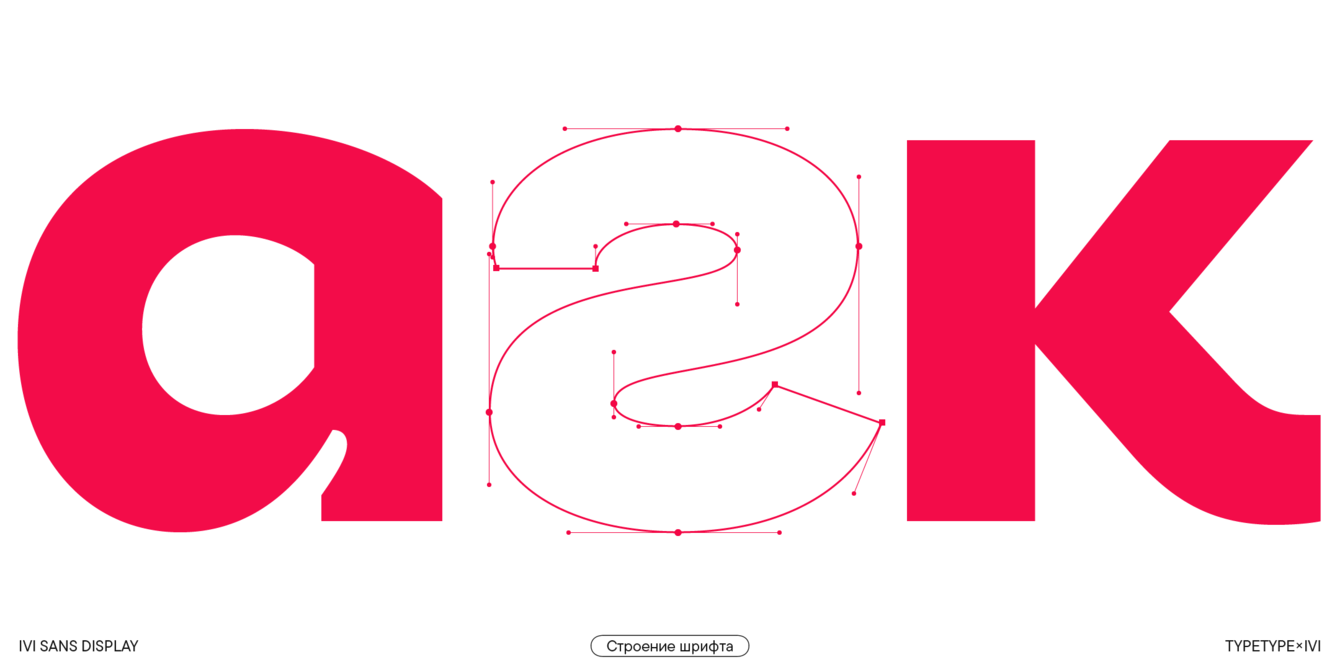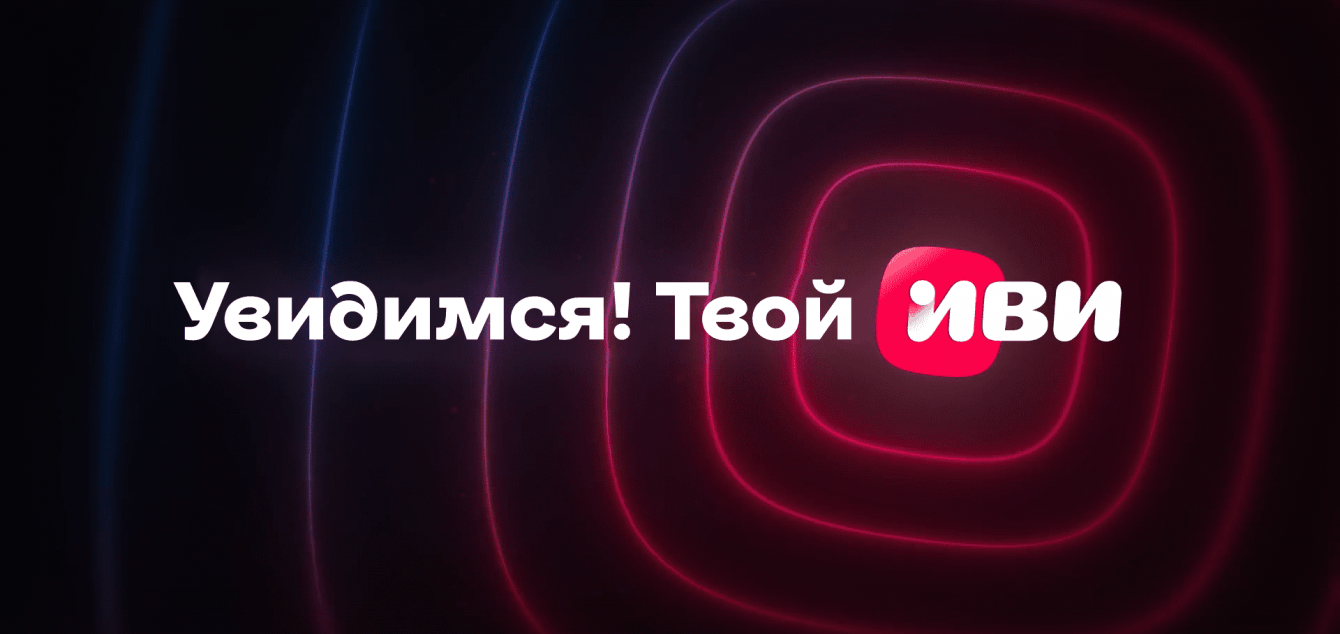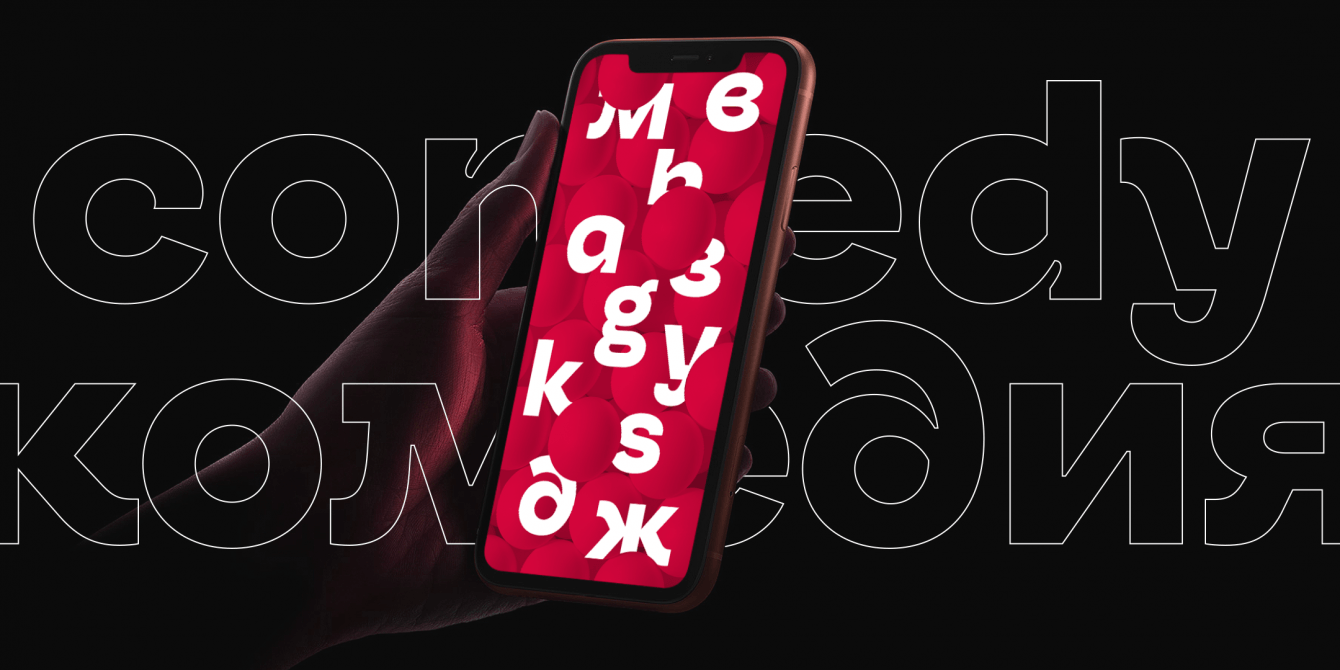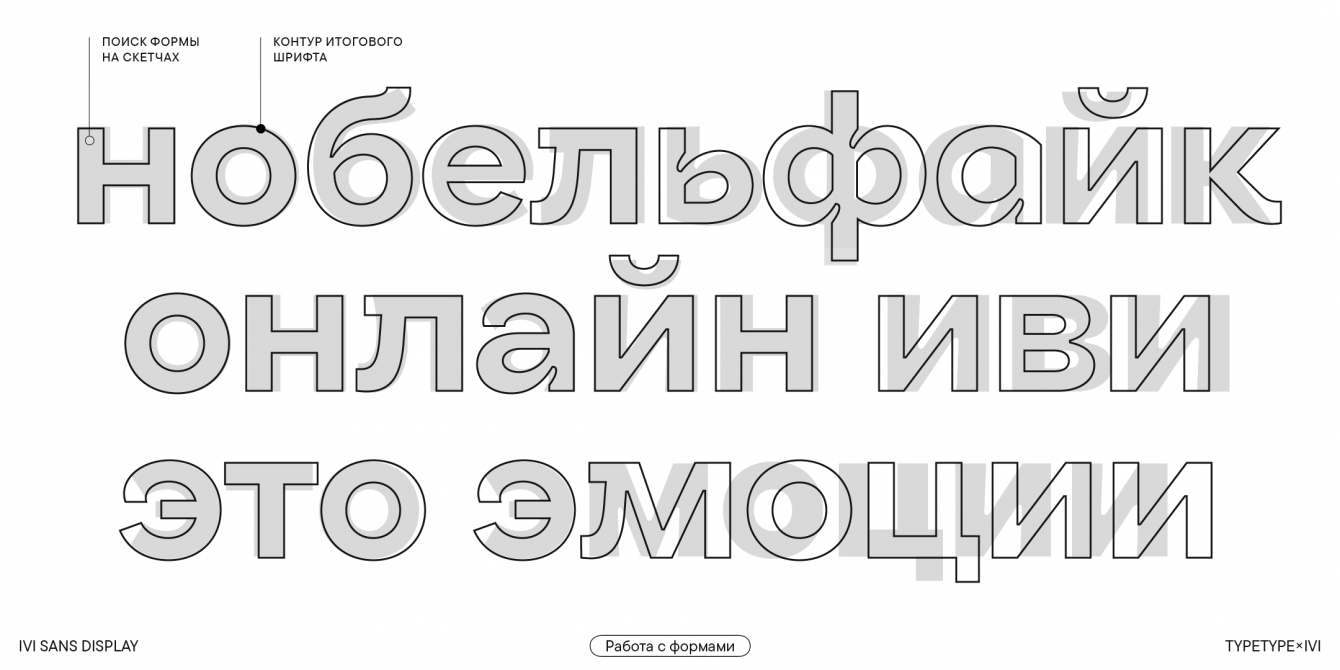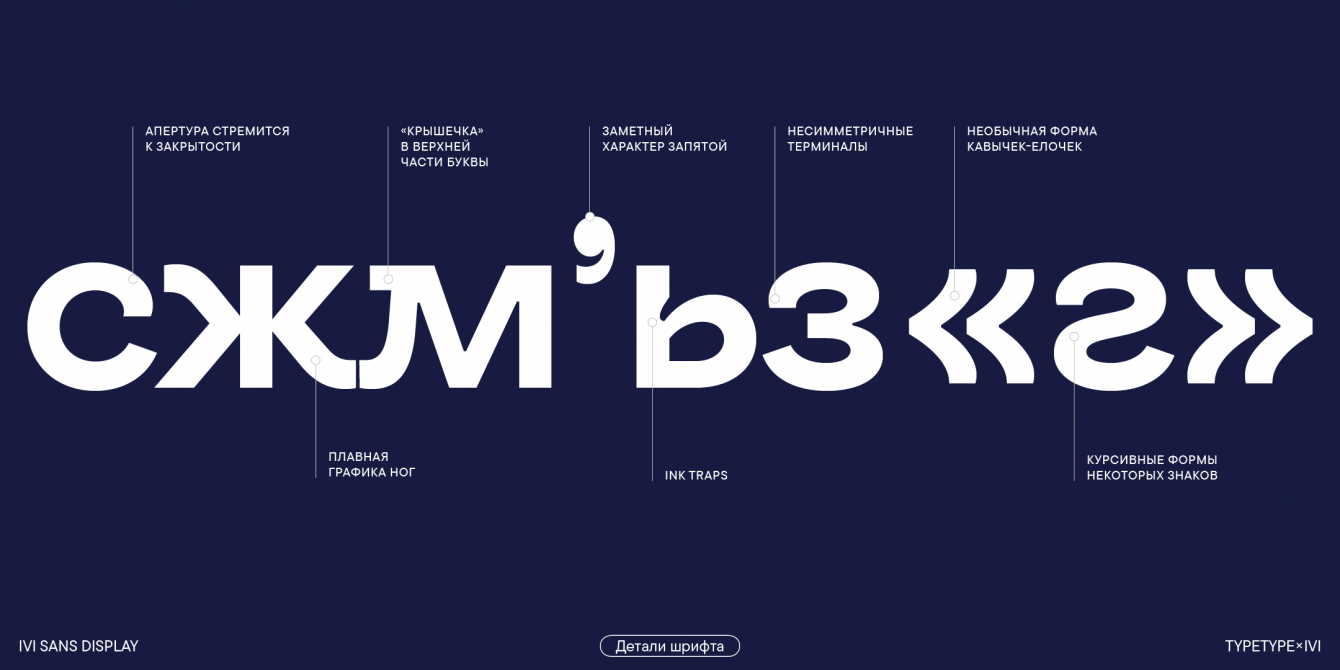
Ivi Sans Display — новый фирменный шрифт онлайн-кинотеатра Иви
Задача
Команда Иви обратилась к нам в поисках фирменного шрифта. После ребрендинга айдентика онлайн-кинотеатра стала мягче и дружелюбнее, острые треугольники в логотипе сменились на округлые формы. При этом для всех коммуникаций по-прежнему использовался базовый геометрический гротеск Ivi Sans. Он был удобочитаемым и технологичным, но не подчеркивал новый характер бренда и не соотносился с его ценностями. Поэтому Иви захотелось найти уникальную гарнитуру, которая станет голосом бренда.
Решение
Совместно с командой Иви мы решили создать фирменный шрифт Ivi Sans Display с нуля, не опираясь на существующий. Ориентиром для работы стали шесть прилагательных, определяющих ценности бренда: эмоциональный, современный, мягкий, оригинальный, яркий и добрый. При этом специалисты Иви хотели, чтобы шрифт был асимметричным, «с чудинкой». Для вдохновения дизайнеры TypeType обращались к визуальной айдентике Иви, в частности — логотипу. Так как большая часть коммуникаций происходит на русском языке, все дизайнерские решения опирались на специфику кириллических знаков.
Исходя из этих данных, шрифтовые дизайнеры создали несколько вариантов скетчей, чтобы команда онлайн-кинотеатра могла выбрать из нескольких вариантов наиболее подходящий. Выбранный набросок лег в основу будущего шрифта — так началась работа над Ivi Sans Display.
1Исследования
Для начала специалисты Иви провели два исследования: оценили эмоциональный отклик пользователей на шрифт, который уже использовался в коммуникациях компании, и шрифты, разработанные TypeType. Затем выбранный вариант сравнили со шрифтами конкурентов. Это помогло выяснить, какой «голос» лучше всего подойдет для новой айдентики.
2Реализация
Затем дизайнеры студии начали работу над деталями. В шрифте решили сделать разные варианты начертаний — на то, что это необходимо, указали результаты исследования. Дело в том, что для разных задач дизайнерам нужен шрифт с разными характеристиками. Для одних — более необычные и привлекающие внимание формы, для других — читабельность и простота восприятия. Все это мы объединили в одной гарнитуре, включив в нее три стилистических сета: Readability, в котором почти все акцентные формы «прячутся», но стиль сохраняется, Curly letters с подчеркнутой декоративностью и Soft Character с несколько «рукописным» характером.
С итоговым видом шрифта нам помогло определиться исследование частотности знаков. То есть при разработке характера шрифта мы сделали акцент на те буквы, которые используются чаще других. Менее частоупотребляемые буквы, напротив, сделали более спокойными. Это помогло создать «ровный» по уровню акцидентности набор для каждого слова или фразы.
Результат
В результате у нас получился яркий, приветливый и привлекательный шрифт с округлыми формами, характерными ловушками для чернил и множеством интересных деталей.
Ivi Sans Display — оригинальный и при этом немного знакомый, странноватый и привлекательный, актуальный и удобный в использовании шрифт. Мы добавили разные варианты начертаний, чтобы его легко можно было адаптировать для разных задач. А еще в нем есть налет «рукотворности», который делает шрифт теплым и приветливым.
Гарнитура включает четыре начертания: Regular, Medium, Bold, Black по 411 знаков в каждом и поддерживает 75 языков. Еще мы добавили 12 OpenType фич, среди них — три стилистических сета: Readability, Curly letters и Soft Character.